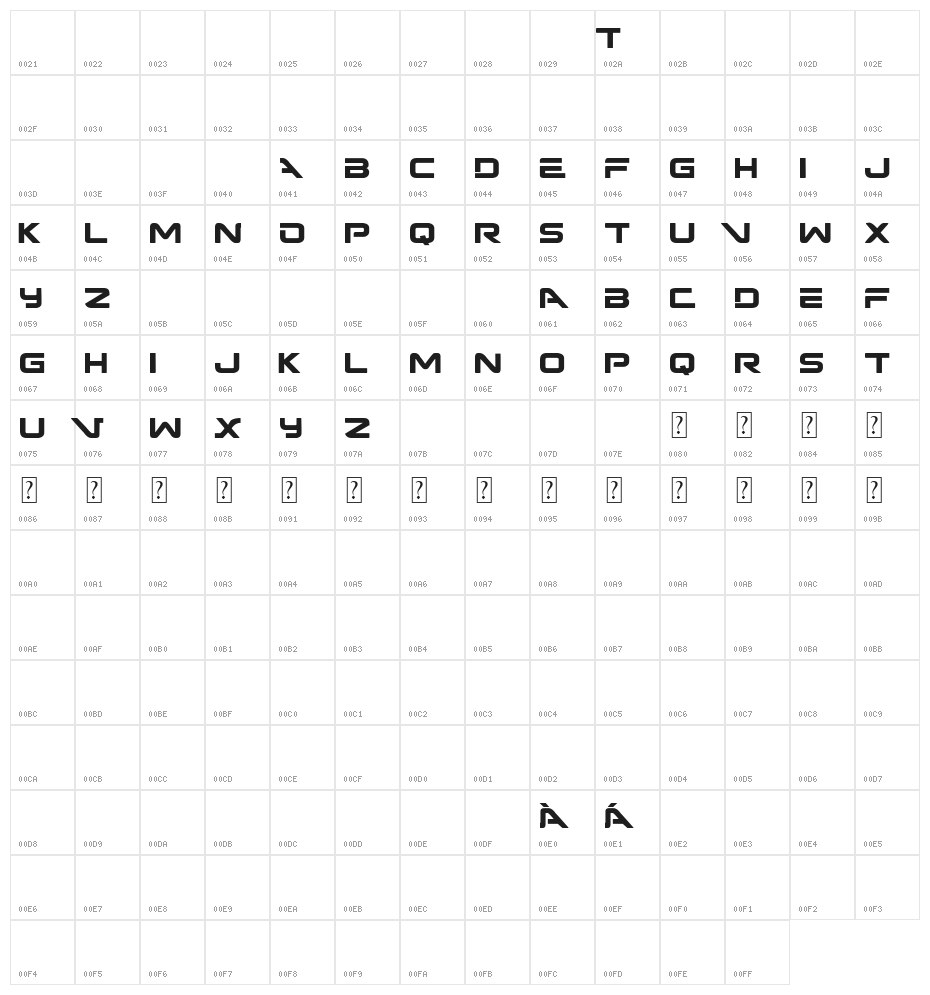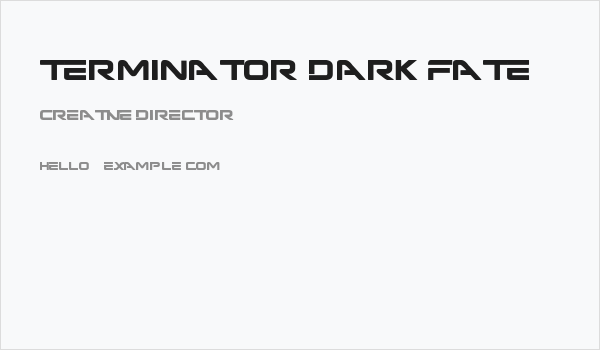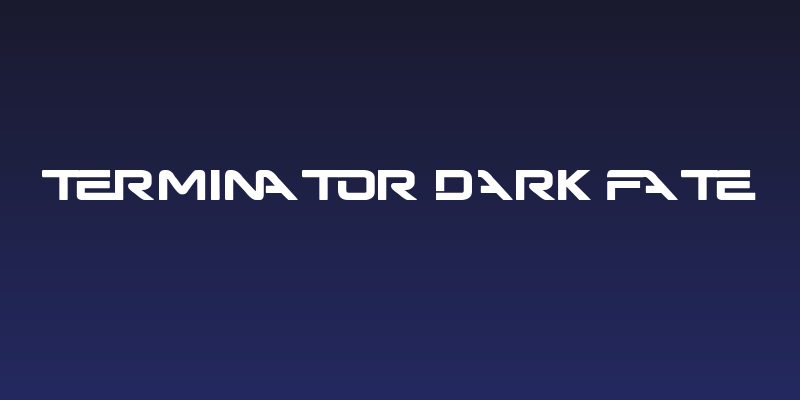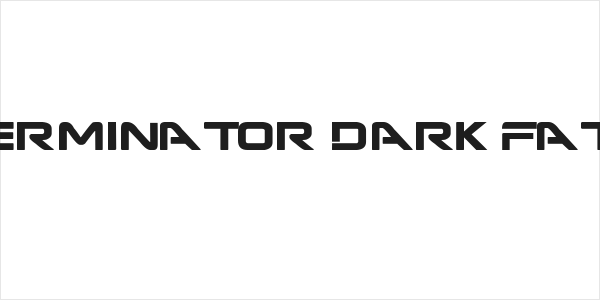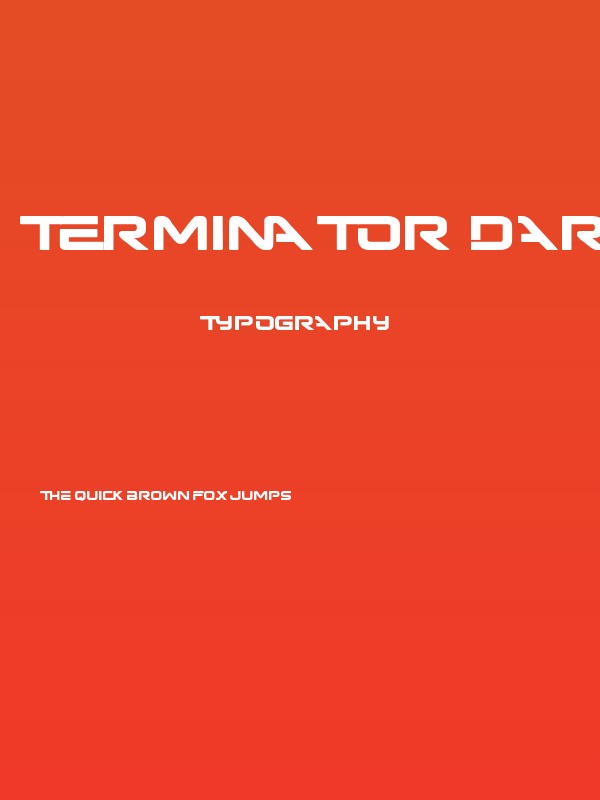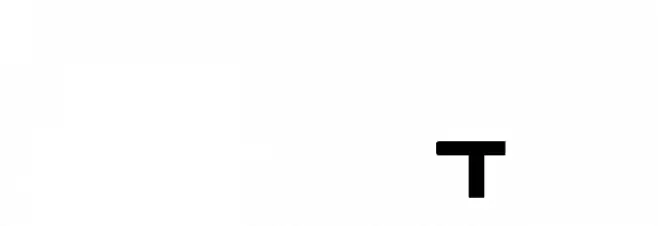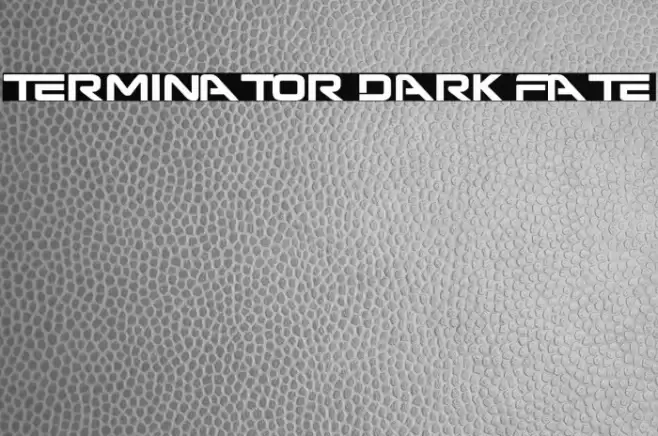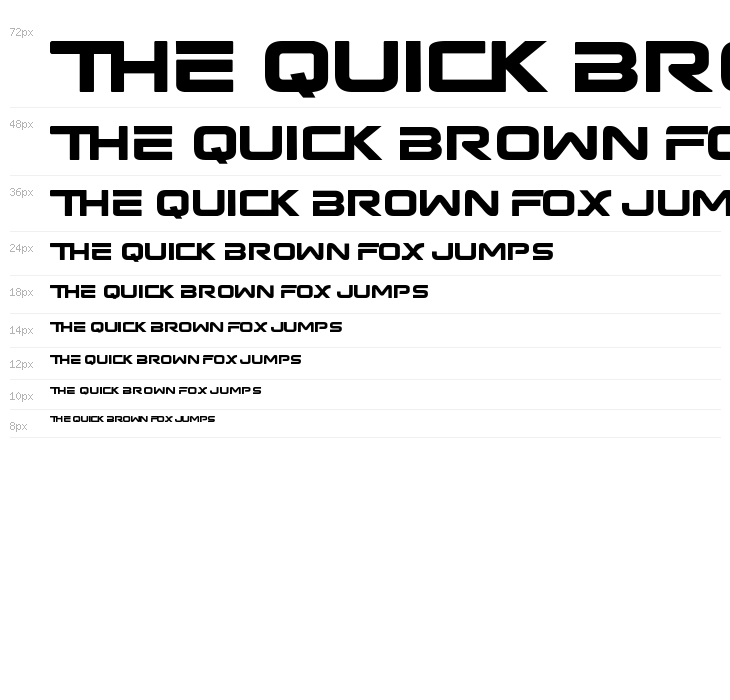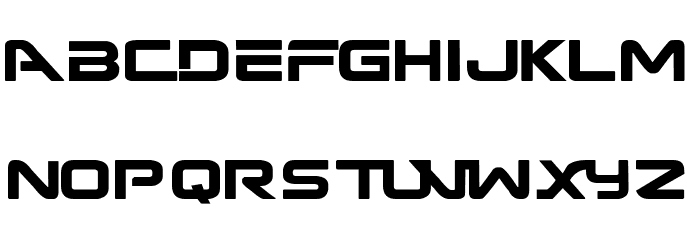
Terminator Dark Fate Font
✎ Futuristic
| Gesamtstil | Futuristic |
| Vorgeschlagene Projekte | Ideal for sci-fi movie posters, video game titles, technology branding, and futuristic-themed designs. |